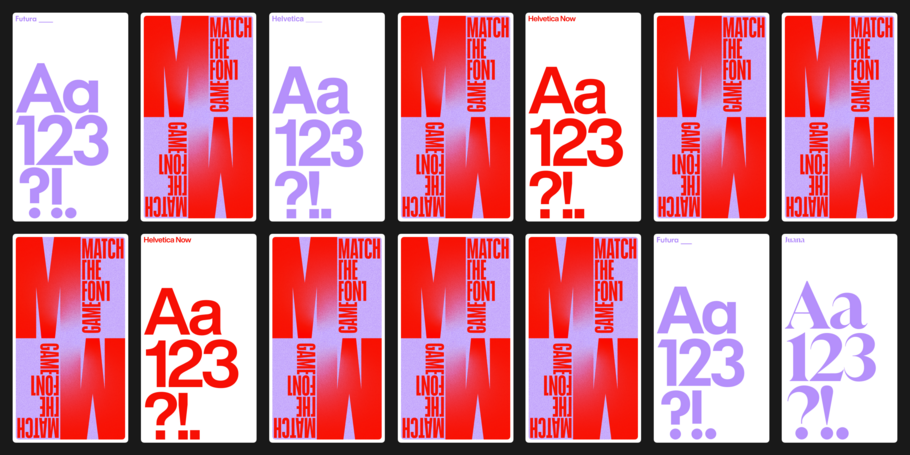
Die Schrift ist der stille Held einer jeden Markenidentität. Von allen Elementen im Branding – einschließlich Form, Farbe, Fotos, Sound und Key-Visuals – ist die Schrift das einzige Element, das Ihre Marke stabil repräsentiert, egal wie reduziert die Botschaft oder wie niedrig aufgelöst das Ausgabemedium ist, von der Smartwatch bis zur Fassadenbeschriftung eines Bürogebäudes.
Die beste Methode, um eine Marken-Kontinuität über alle Kontaktpunkte hinweg zu gewährleisten, ist der konsistente Einsatz einer eigenen Hausschrift, die Ihre Marke unverwechselbar macht. Ungeachtet dieser Tatsache kommt es immer wieder zu Schriftstörungen oder zu einem Austausch der verwendeten Fonts, sogar überraschend häufig. Das liegt vor allem daran, dass die digitale Kommunikation eine Menge Fehlerquellen in sich birgt. Jedes Mal, wenn eine Schriftdatei in Ihr Marken-Ökosystem gelangt oder es verlässt, besteht die Gefahr, dass ein Text plötzlich anders aussieht als er eigentlich sollte.
Wenn Sie im Schriftbild Ihrer Marke Ungereimtheiten feststellen oder befürchten, dass typografische Schnittstellen unterbrochen sind – keine Panik: So etwas kommt vor, und meistens gibt es dafür eine einfache Erklärung. Wir haben in jedem Fall auch die passende Lösung für Sie. Aber lassen Sie uns zunächst einen Blick auf einige der häufigsten Ursachen für Schriftinkonsistenzen werfen.
Häufige Ursachen für Schriftinkonsistenzen
- Verwendung unterschiedlicher Schriften in Print und Online. Für die Arbeit mit Fonts am Schreibtisch gelten oft andere technische Anforderungen als für die Website-Gestaltung. Es gibt Unterschiede in den Zielmedien und den sich daraus ergebenden Kriterien für die Lesbarkeit, und nicht selten unterliegen die im Desktop-Kontext verwendeten Schriften anderen Lizenzbedingungen. Eine Marke, deren Identität sich über Jahrzehnte hinweg in der analogen Welt entwickelt hat (und nur in dieser), arbeitet möglicherweise mit Schriften, die es im Web-Font-Format (noch) nicht gibt. So kommt es, dass online und offline oft verschiedene Schriften verwendet werden.
- Wechsel zwischen verschiedenen Schnitten oder Stilen derselben Schrift. Viele Schriften sind in einer großen Anzahl von Varianten auf dem Markt. Ein Beispiel: Neue Helvetica, eine der beliebtesten Schriftfamilien der Welt, hat 59 (!) Schnitte. Auf vielen Computern ist die Standard-Helvetica installiert, die anders spationiert ist und deren Zeichen sich in vielen Details von denen anderer Varianten unterscheiden. Da kann es leicht passieren, dass ein Agenturpartner statt Neue Helvetica Bold die „alte“ Helvetica Bold verwendet oder statt Neue Helvetica Compressed Light zur Variante Compressed Thin greift.
- Produktion von Arbeiten in mehreren Sprachen. Marken, die in neue Regionen expandieren, benötigen oft zusätzliche Sprachunterstützung und erweiterte Zeichensätze, die in der Hausschrift nicht immer verfügbar sind. Als Notlösung greifen viele zu einer besser ausgebauten Schrift, die der ursprünglichen zwar ähnlich, aber nicht mit ihr identisch ist.
- Inkonsistente oder unzureichende Lizenzierung von Schriften. Ohne eine gut durchdachte Strategie für die Lizenzierung von Schriften kann es vorkommen – ob unabsichtlich oder nicht, das spielt für Urheberrechtsverletzungen keine Rolle –, dass Marken Schriften für Verwendungszwecke einsetzen, für die sie gar nicht lizenziert sind. Niemand sollte davon ausgehen, dass die Desktop-Lizenz einer Schrift auch deren Benutzung in digitalen Umgebungen einschließt, also auf der Website, in einer App oder für einen HTML-Newsletter. Details dazu finden sich in der Endbenutzer-Lizenzvereinbarung (EULA), die es zu jeder Schrift gibt. Aber wer kennt diese schon im Einzelnen?
Für wen besteht die Gefahr von Schriftinkonsistenzen?
Für manche Unternehmen ist das Risiko von Schriftinkonsistenzen größer als für andere. Wenn Ihre Marke keine klare Philosophie und keinen klaren Prozess für die Beschaffung, Verwaltung und Lizenzierung von Schriften definiert hat, ist es wahrscheinlicher, dass sich in der täglichen visuellen Kommunikation Inkonsistenzen einschleichen. Ein Beispiel: Wie sieht der Übergabeprozess aus, wenn Mitarbeiter das Unternehmen verlassen? Wenn es dafür keinen Plan gibt, der auch das Thema Fonts umfasst, ist es wahrscheinlich, dass ein neuer Mitarbeiter nicht über das nötige Hintergrundwissen verfügt, um die richtigen Entscheidungen bezüglich der verwendeten Schriften zu treffen. Ein anderes Beispiel: Wie ist die Font-Lizenzierung bei der Kooperation mit Druckereien, Lieferanten und Agenturen geregelt? Wenn es dafür keinen klar definierten Prozess gibt, kann es sein, dass man sich – bewusst oder unbewusst – einem potenziellen rechtlichen Risiko aussetzt; es kann auch sein, dass Ihre externen Partner nicht über die notwendigen Lizenzen verfügen und in der Folge Fonts ausgetauscht werden müssen. Kümmert sich die Agentur, mit der Sie zusammenarbeiten, um den Download und das Lizenzieren von Schriften? Wenn ja, ist die Font-Strategie Ihrer Marke nicht mehr zentralisiert und es können Weichen gestellt werden, die sich Ihrer Kontrolle entziehen.
Der Schlüssel zur Vermeidung und Lösung solcher Schriftinkonsistenzen ist die Entwicklung einer klaren Schriftstrategie. Es kann ein ungeheurer Aufwand sein, ein Schriftproblem zu lösen, das bereits weit im Unternehmen verbreitet ist, viele Unbekannte enthält und möglicherweise schon lange besteht. Aber eine methodische Untersuchung und Lösung ist möglich. Hier ist der beste Weg dorthin:
- Identifizieren Sie alle Font-Unstimmigkeiten und untersuchen Sie sie gründlich. Dokumentieren Sie, wo sie auftreten, wer von ihnen betroffen ist, wer an der Entstehung der Unstimmigkeiten beteiligt war und warum. Es ist wichtig, das komplette Ausmaß des Missstandes zu verstehen, bevor Sie Maßnahmen zu seiner Lösung ergreifen.
- Übertragen Sie einer Person in einer funktionsübergreifenden Rolle die volle Verantwortung für das Font-Management. Am besten ist es, wenn diese Person die Sprache der Kreativen versteht und mit der Vision Ihrer Marke bestens vertraut ist. Zugleich sollte sie sich aber auch mit Budgets und dem internen Workflow auskennen. In der Regel ist das jemand aus der IT oder dem Einkauf.
Eine solche Person zu finden, kann eine Herausforderung sein, da es selten vorkommt, dass Menschen aus so unterschiedlichen Bereichen des Unternehmens eng genug zusammenarbeiten, um alle gerade genannten Kenntnisse in einer Person zu vereinen. (Laut Adobes Bericht „Digital Trends 2022“ glauben nur 33 Prozent der befragten Mitarbeiter, dass ihre Marketing- und IT-Leute eng genug zusammenarbeiten, um eine Bewertung von 8/10 zu verdienen). Doch die Mühe lohnt sich. Denn eine mangelnde Kooperation zwischen den Abteilungen führt langfristig gesehen fast zwangsläufig zu einer divergierenden Markenphilosophie. Eine teamübergreifende Kommunikation hingegen wirkt sich unmittelbar positiv auf die konsistente Markenstimme aus – nach innen und nach außen.
Ein cloudbasiertes Font-Management ist der ideale Weg, um die Synchronizität von Schrift-Beschaffung, -Bereitstellung und -Lizenzierung zu gewährleisten. Das richtige Tool für die Schriftverwaltung erleichtert Ihnen das Leben, indem es den Benutzerzugriff auf Fonts automatisiert, die Lizenzierung rationalisiert und die Schriften mit den bevorzugten Programmen Ihres Kreativteams synchronisiert. Die Zentralisierung der Font-Verwaltung unter einem einzigen Dach löst nicht nur alle gegebenenfalls bestehenden Probleme, die in der Vergangenheit zu typografischen Inkonsistenzen geführt haben, sondern stellt vor allem auch sicher, dass diese in der Zukunft erst gar nicht mehr auftreten.